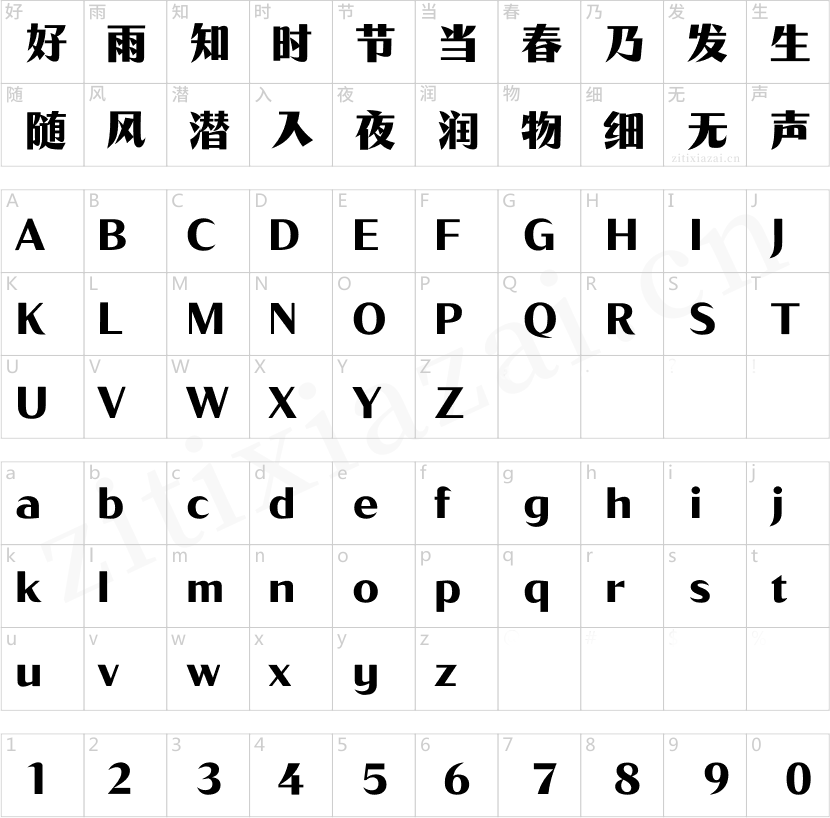
Aa锐智体
Aa锐智体,这款字体结构工整、笔画清晰,兼顾美观与易读性,适用于标题、正文、海报、包装、LOGO 等多种场景。字形优雅稳定,风格百搭耐看,适配日常排版与创意设计,让文字呈现更舒适、更具质感。Aa锐智体一笔一画,皆是细节,以均衡的比例、流畅的线条打造舒适视觉体验,字形端正大气,风格简约现代。无论是商业设计、品牌宣传还是日常排版,都能轻松驾驭,让文字更有格调与力量。Aa锐智体字体下载。
Aa锐智体是一款非常具有艺术性的字体,它的设计灵感来源于对古典艺术的研究,同时又融入了现代字体设计的元素。字形优美,笔画粗细变化自然,给人以大气、典雅的感觉。Aa锐智体是一款既传统又现代的字体,它的设计充满艺术感,美观大方,实用性也非常强。无论是对于设计师还是对于普通读者来说,都是一种非常不错的字体选择。Aa锐智体适合用于具有艺术感的场合,比如海报、宣传单张、书籍封面等。由于其字形流畅且具有动态感,也适合用于大量的文本排版,如报纸、杂志等。
• 字体名称:Aa锐智体
• 字体标识:1.000;Aa;AaRuiZhiTi;2022
• 字体全名:Aa锐智体
• PostScript:AaRuiZhiTi